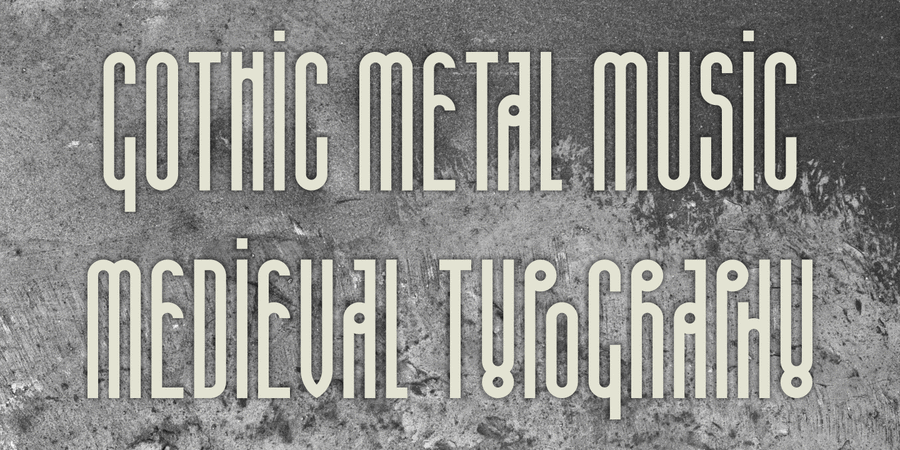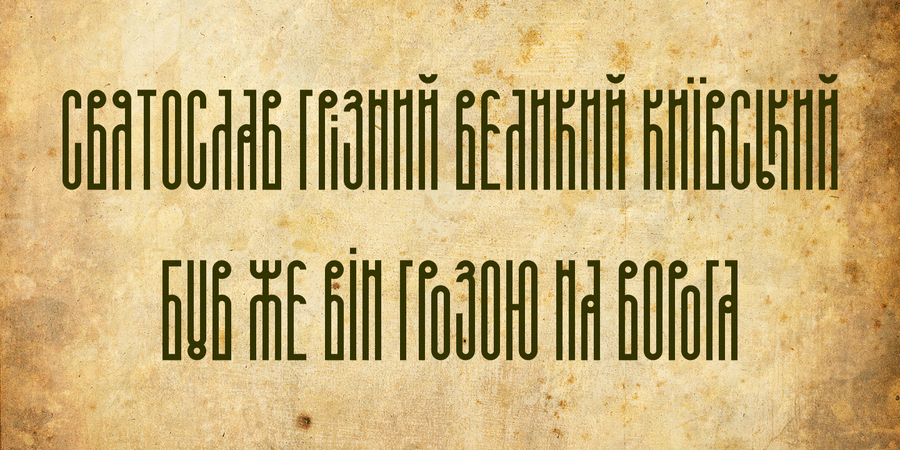
Аскетик 2D - декоративный шрифт, основанный на кириллической вязи XV-XVI вв. Буквы такого типа использоваться для акциденции в сакральных текстах. Характерным для вязи является подгонка букв друг к другу так, чтобы выглядело все одним сплошным орнаментальным фризом. Шрифт богат дискретными лигатурами, что помогает лучше раскрыть стиль вязи. Кроме букв и других стандартных символов есть ряд монограмм и христианских символов. Эти и другие функции доступны в OTF формате. Шрифт разработали Данил Турецкий и Лукьян Турецкий для студии 2D Studio в 2010 году.
tall, close-fitting, religious, church, orthodox christian, distinctive, original, notable, slim, playful, splashy, musical, voiced, solid, accurate, flat, architectural, mysterious, occult, mystical, strange, exotic, biblical, Christian, sacral, presents, experimental